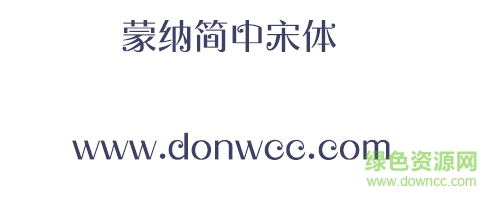
蒙納簡中宋電腦排版字體是一款專為pc經(jīng)常需要進行排版的朋友打造的字體,該字體中規(guī)中矩,非常適合上班經(jīng)常需要正規(guī)文件的用戶實用需要的朋友趕緊來綠色資源網(wǎng)下載吧
宋體,是為適應印刷術(shù)而出現(xiàn)的一種漢字字體。筆畫有粗細變化,而且一般是橫細豎粗,末端有裝飾部分(即「字腳」或「襯線」),點、撇、捺、鉤等筆畫有尖端,屬于襯線字體(serif),常用于書籍、雜志、報紙印刷的正文排版。